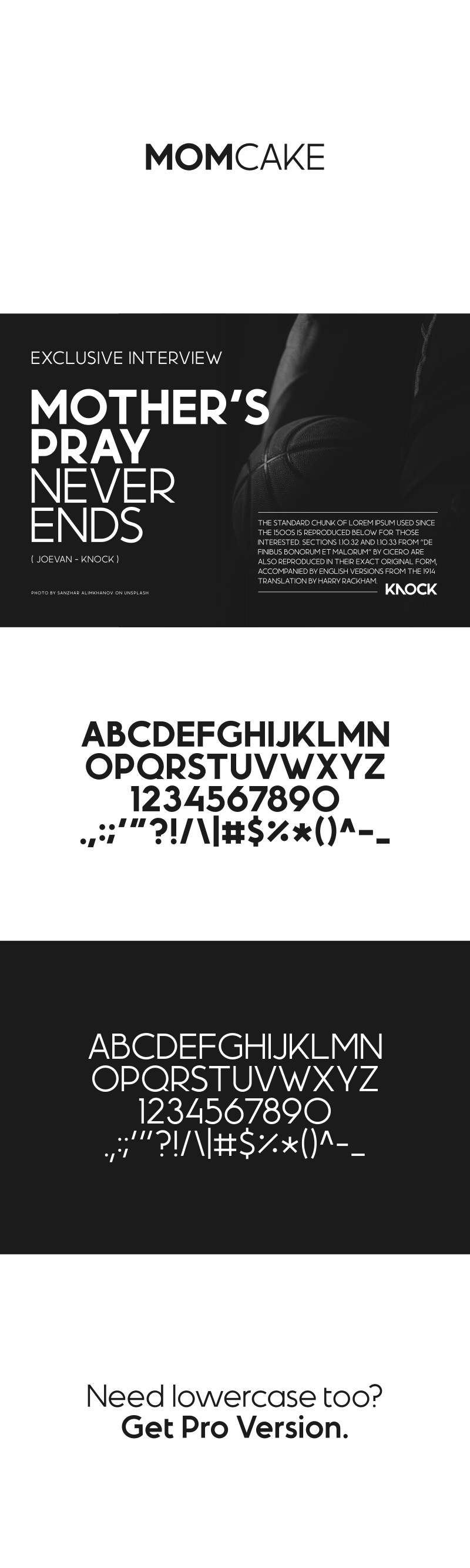
Font Help!!! Momcake pro
Momcake pro font තියෙන ප්න්වතෙක් ඉන්නවද? මේකේ ෆ්‍රී වර්ශන් එක සිම්පල් අකුරු දෙන්නෙ නෑ. කැපිටල් විතරයි. ප්‍රෝ එකට දෙකම දෙනවා. තියෙන පින්වතෙක් දියංකෝ!! 😊😊😊
තෑන්ක්ස් බන් . ඒත් මේක ෆ්‍රී එක මචන් ඕන ප්‍රො එක. මේකේ තියෙන්නෙ කැපිටල් අකුරු විතරයි. 😐😐 ප්‍රෝ එකේ දෙකම තියේ. මේ තියෙන්නෙ ෆොන්ට් එක.
Simple එකේ JPG එකක් නැද්ද? හයි කොලිටි එකක් තිබ්බ නම් ඒක වෙක්ටර් කරලා ගන්න තිබ්බ.